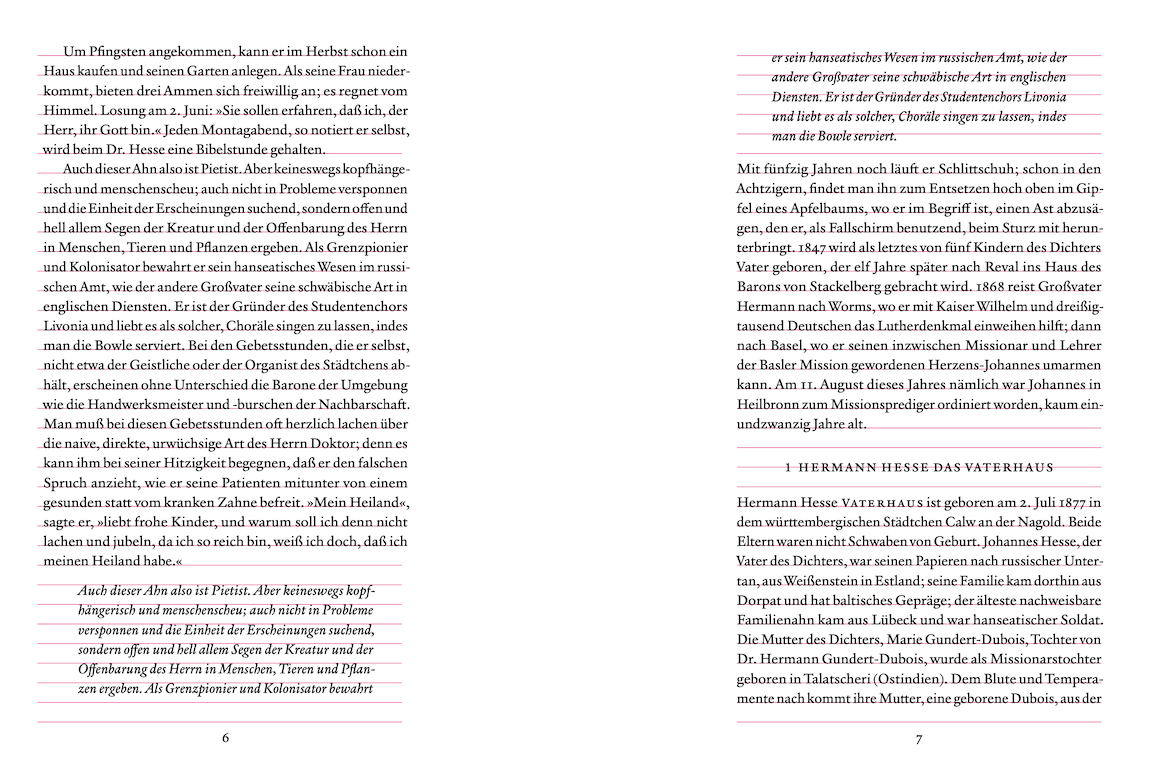
Triviale Frage zur Wiederherstellung der Registerhaltigkeit nach Einschüben
Manchmal kommt es vor, daß beim Seitenumbruch nicht-registerhaltige Einschübe, wie Listen, Definitionen, oder Zitatblöcke, zweigeteilt werden.  Ich kenne keine typographische Regel, der dies zuwiderliefe.
Hier ein Beispiel:
Daß der Einschubteil auf der Versoseite etwas über der letzten Grundlinie endet, stört mich eher wenig. Was Forssman und de Jong dazu auf Seite 74 ihrer Detailtypografie (2.Aufl.) sagen, habe ich wohl nicht verstanden. Sie scheinen zu fordern, die letzte Zeile des Einschub(teil)s hier auf eine Zeile des Grundlinienrasters zu stellen. Würde das nicht bei gleichbleibendem Zeilenabstand den Weißraum über dem Einschub störend vergrößern bzw. verkleinern?
Auf der Rectoseite setze ich die erste Zeile des Einschubteils etwas tiefer als die Grundlinie, sodaß die Registerhaltigkeit des folgenden Textes gewahrt bleibt.
Ist dies der übliche, bzw. ein akzeptabler Umgang mit einer solchen Situation?  Oder stehend dem andere ästhetische Aspekte der Doppelseite entgegen? Ich frage, weil ich derzeit versuche, dies in LaTeX zu erzwingen, was mir nicht wirklich gelingt. Obiges Bild ist Resultat eines mutmaßlich praxisuntauglichen Pfusches.
(Diese Lösung schaut m.E. auch etwas blöde aus, wenn die Versoseite mit einem Abschnittstitel und die Rectoseite mit einem Einschub beginnt, falls (wie in diesem Dokument) Titel und Einschübe  verschieden tief gestellt sind. Man hat dann im Dokument zumindest drei Arten verschieden hoch positionierter Anfangszeilen.)
Das Setzen von ganzen Leerzeilen vor und nach Abschnittstiteln und Einschüben würden natürlich alle diese Probleme bzgl. Registerhaltigkeit in einfachster Weise verschwinden lassen. Ich finde solche Abstände allerdings meist viel zu groß und ästhetisch unbefriedigend (auch wenn das in Bringhursts Elements funktioniert hat).  Ist dies nachvollziehbar, oder bin ich hier »visuell irregeleitet«?
Mir ist der Abstand dann zu groß. Noch irritierender finde ich die Plazierung der kursiven Unterabschnitte. Die liegen mir dann ebenfalls zu hoch.
Einen Blindtext zum Vergleich der beiden Versionen habe ich angehängt. Alles ist noch unfertig. Derzeit geht es mir nur um die vertikalen Abstände und die Registerhaltigkeit. Ich bin für jede weitere Kritik dankbar.
Ich bin mir auch unsicher, ob der ZAB nicht etwas zu großzügig ist. Der getönte Bereich soll das Papierformat darstellen.
Die Kursive wurde bewusst weggelassen?
Unbewußt. Auch die Breite des Zitats  ist wohl zu eng. Die diversen Vertikalabstände sind, wie gesagt, was mich derzeit einzig interessiert.